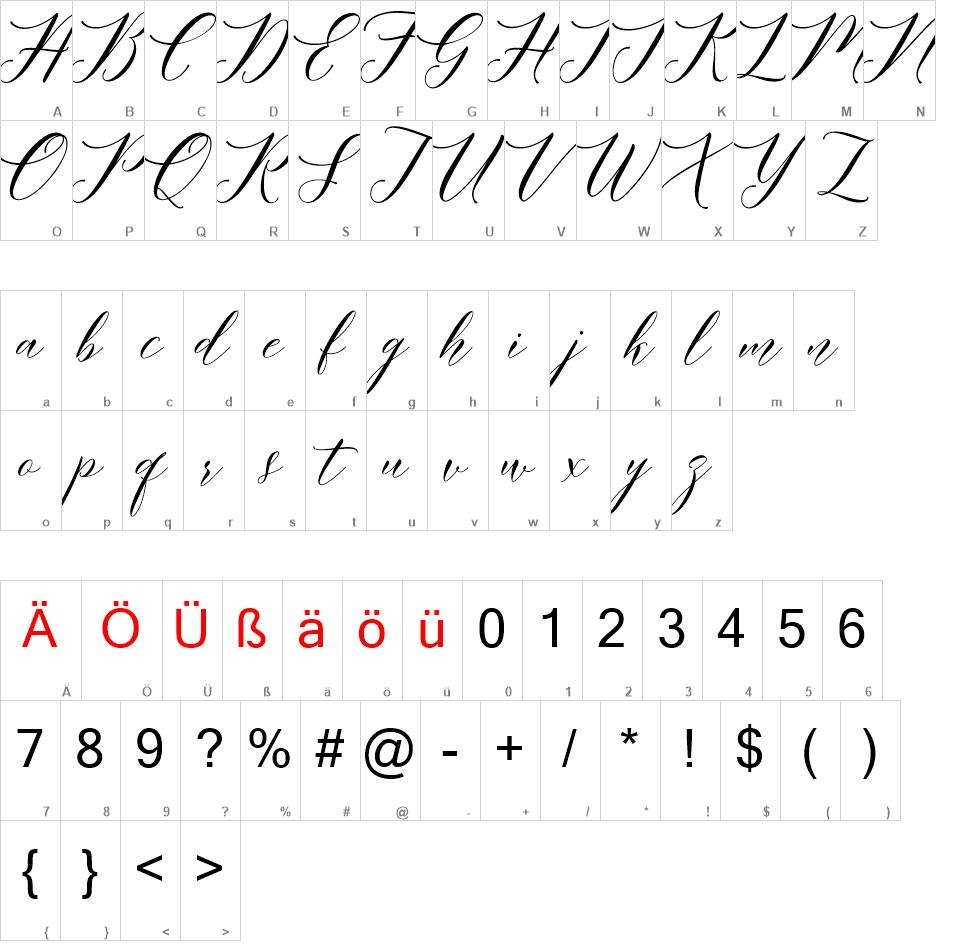
Einführung von Meetha Script
Meetha Script ist eine moderne Kalligrafieskriptschrift. Dies ist eine schöne Skriptschriftart mit kursivem Stil. Gemacht und getanzt, um den Charakter des modernen Schreibens zu geben, das süß, einfach, stilvoll und fest ist.